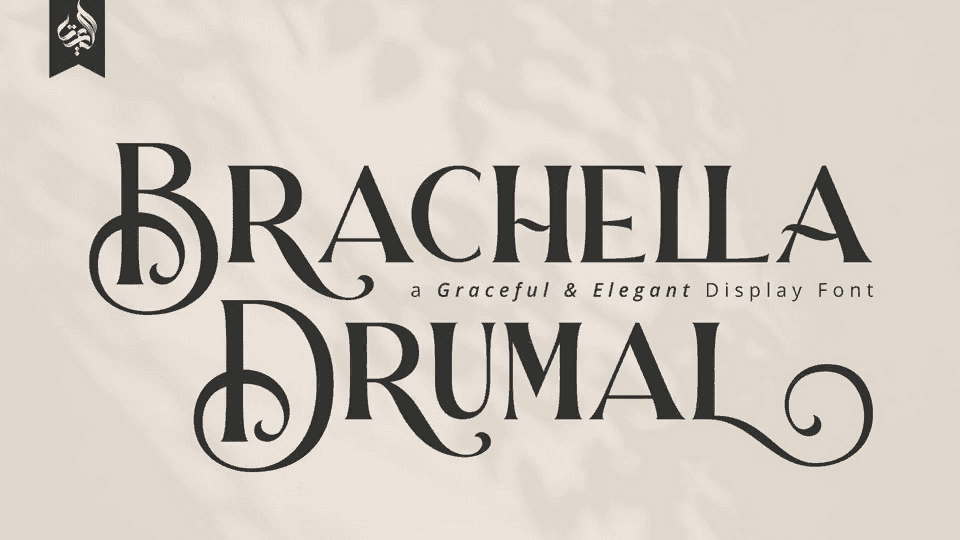
Название: Brachella Drumal Font (2021)
Brachella Drumal, изящный и элегантный шрифт для отображения текста.
30+ потрясающих альтернатив и лигатур для создания мистического, красивого, стильного, элегантного дизайна.